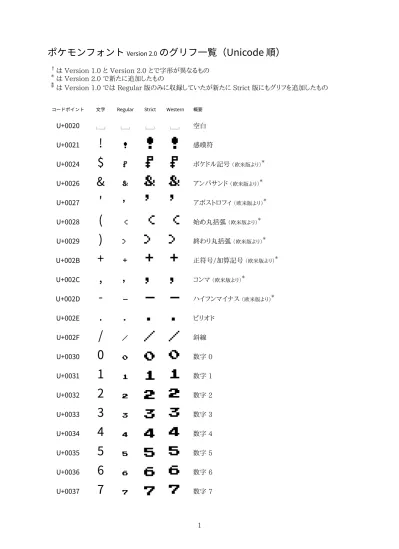
ポケモンフォント
のグリフ⼀覧(Unicode 順)
†は Version 1.0 と Version 2.0 とで字形が異なるもの * は Version 2.0 で新たに追加したもの
** は Version 1.0 では Regular 版のみに収録していたが新たに Strict 版にもグリフを追加したもの
コードポイント ⽂字 Regular Strict Western 概要
空白U+0021
感嘆符U+0024
ポケドル記号(欧米版より)*U+0026
アンパサンド(欧米版より)*U+0027
アポストロフィ(欧米版より)* U+0028(
始め丸括弧(欧米版より)* U+0029)
終わり丸括弧(欧米版より)* U+002B+
正符号/加算記号(欧米版より)* U+002C,
コンマ(欧米版より)* U+002D-
ハイフンマイナス(欧米版より)* U+002E.
ピリオド U+002F/
斜線 U+00300
数字 0 U+00311
数字 1 U+00322
数字 2 U+00333
数字 3 U+00344
数字 4 U+00355
数字 5 U+00366
数字 6 U+00377
数字 7U+0038
数字 8 U+00399
数字 9 U+003A:
コロン U+003B;
セミコロン(欧米版より)* U+003F?
疑問符 U+0040@
モンスターボール U+0041A
ラテン文字 A U+0042B
ラテン文字 B U+0043C
ラテン文字 C U+0044D
ラテン文字 D U+0045E
ラテン文字 E U+0046F
ラテン文字 F U+0047G
ラテン文字 G U+0048H
ラテン文字 H U+0049I